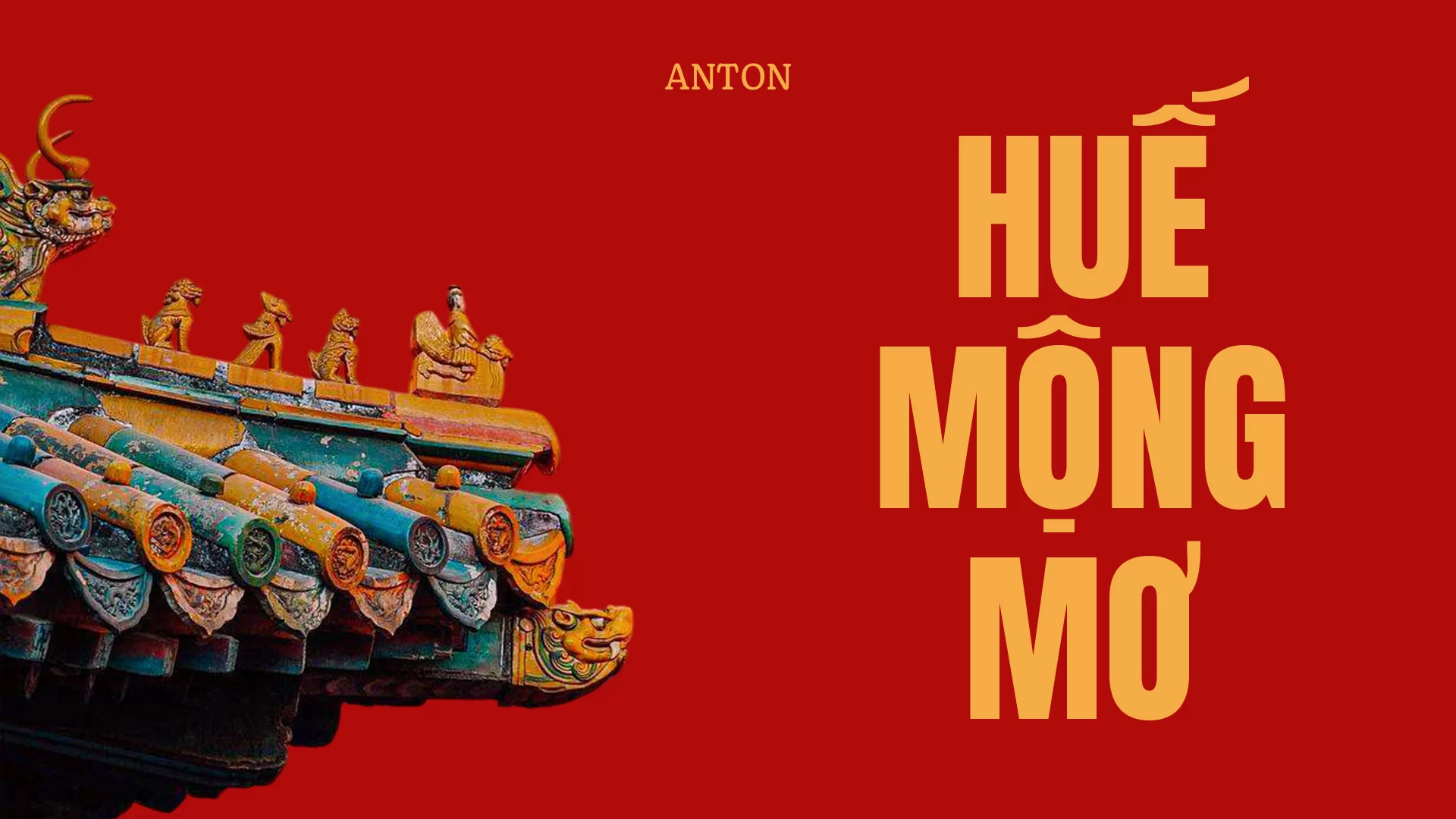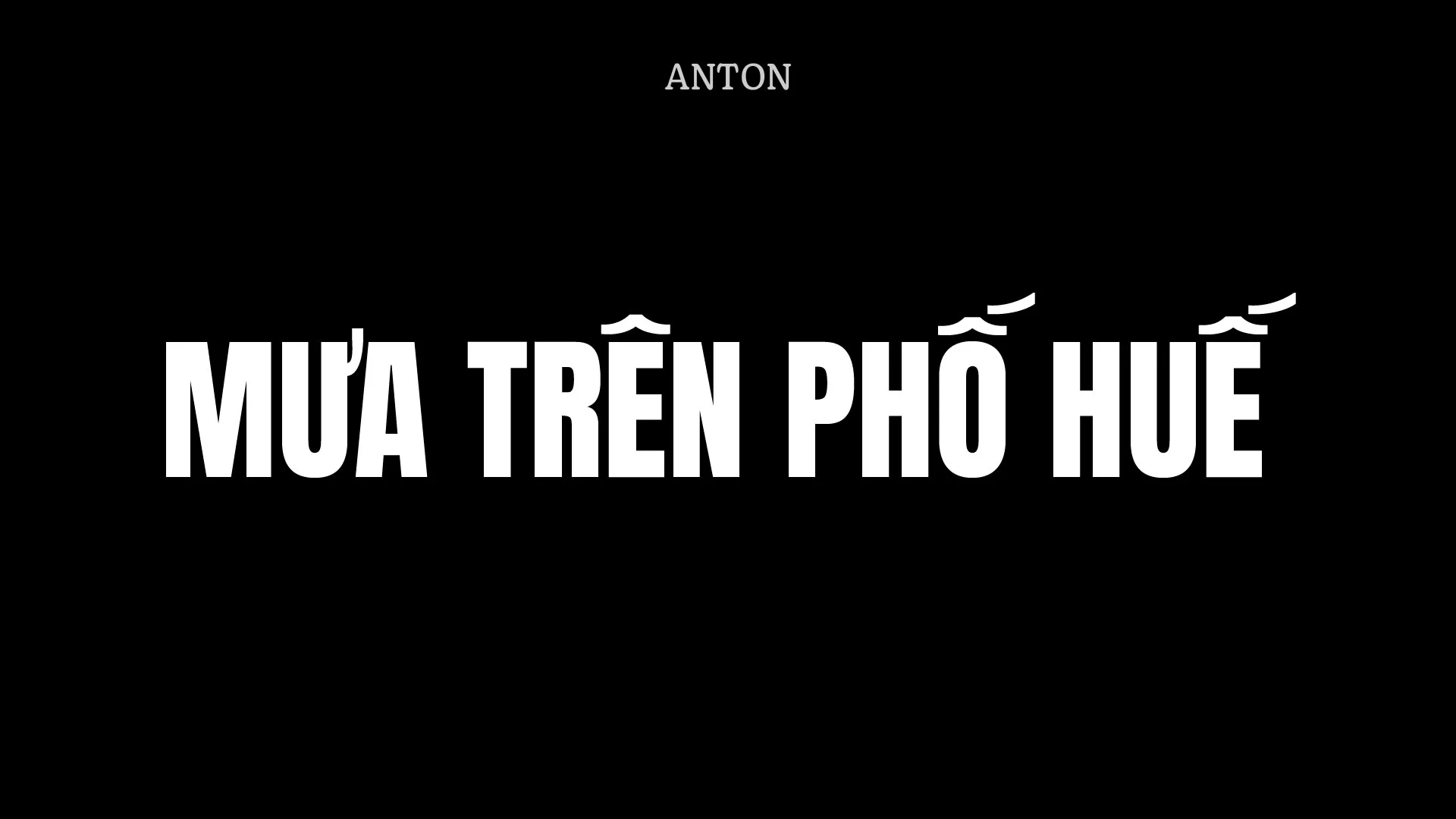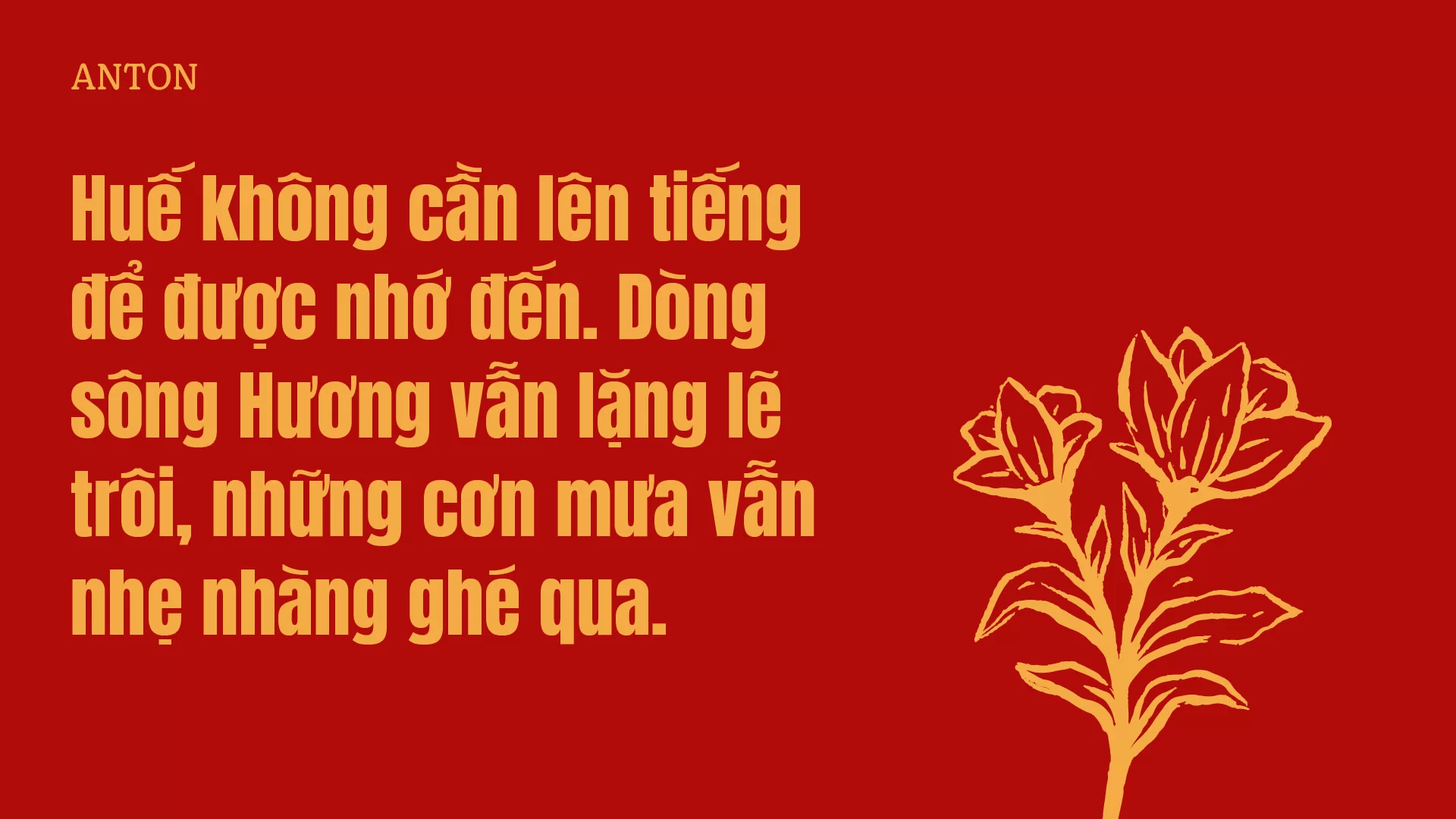
PS Anton – Font Display Việt Hoá tốt cho tiêu đề
Anton được thiết kế bởi Vernon Adams với tỷ lệ rộng và độ đậm lớn, tạo nên sức hút thị giác mạnh ngay từ cái nhìn đầu tiên. Đây là lựa chọn quen thuộc cho headline, quảng cáo, thumbnail YouTube và các thiết kế cần khả năng đọc nhanh, nổi bật ở kích thước lớn.